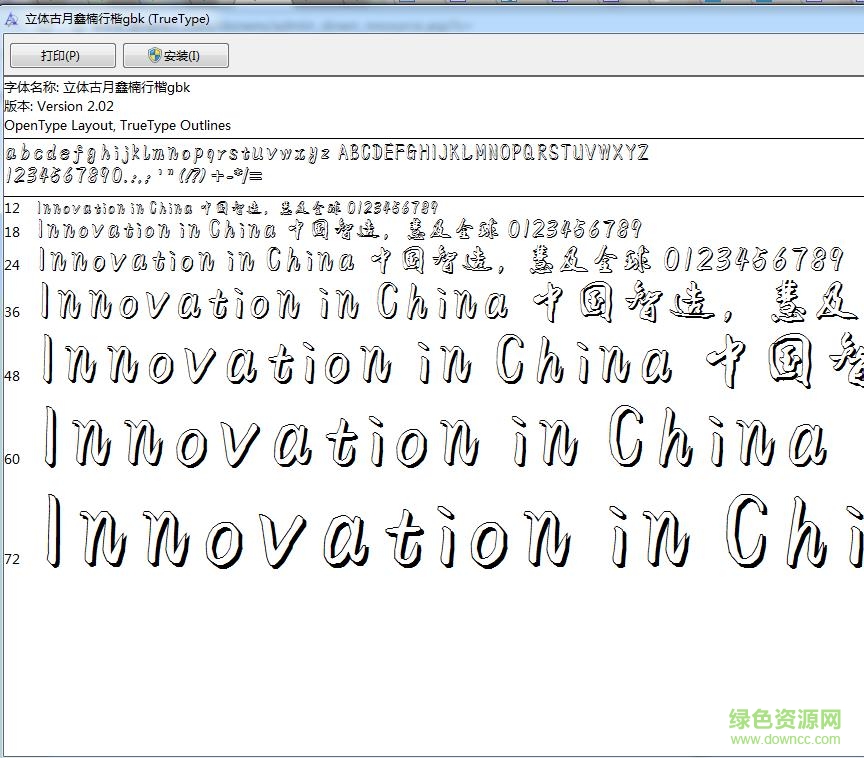
立體古月鑫楠行楷gbk字體十分的古典雅致,蘊(yùn)含了讓你心馳神往的古風(fēng)氣韻,讓你在使用的同時(shí)感受到無(wú)窮的視覺享受,仿佛回到了古代體驗(yàn)毛筆書法字體時(shí)的樂趣,能夠?yàn)橛脩魧?shí)現(xiàn)眾多字體表現(xiàn)效果,快來綠色資源網(wǎng)下載吧!
楷書
楷書在書法字體結(jié)構(gòu)方面,與隸書差不多,但楷書將隸書筆劃的寫法改變了,且由扁形的隸書改為基本上呈現(xiàn)方形的楷書,即所謂的方塊字。